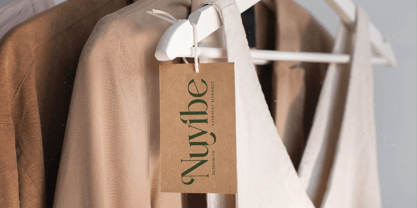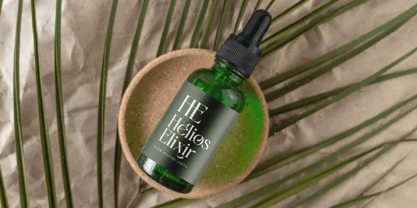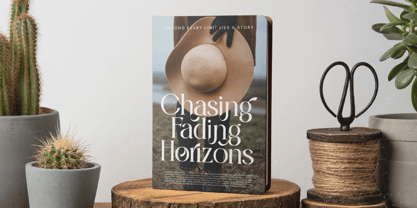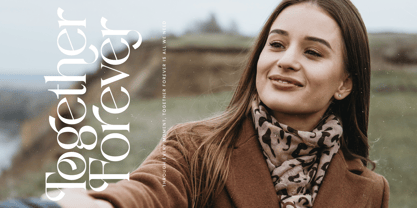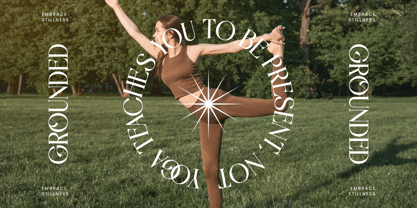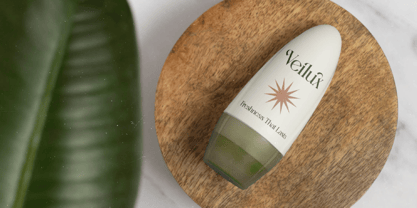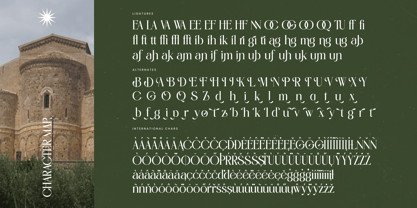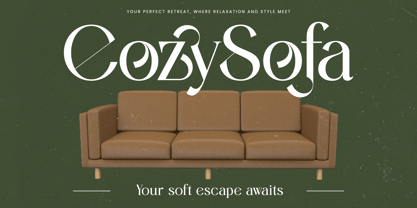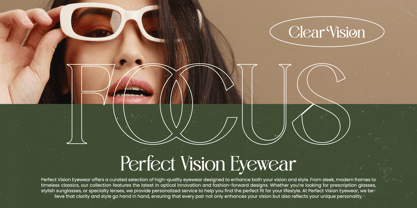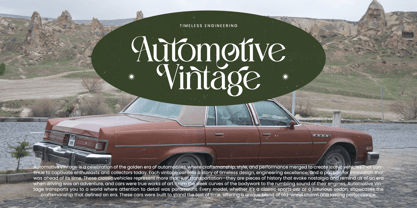
Kinetic Bravely
La familia tipográfica Kinetic Bravely fue diseñada por Heru Utama Putra y publicada por Timelesstype Studio. Kinetic Bravely contiene 2 estilos y opciones de paquete familiar. Más información sobre esta familia
Kinetic Bravely - Bold Tall Serif Font , from Timelesstype, Suitable for any projects such as: logos, branding projects, homeware designs, product packaging, mugs, quotes, posters, shopping bags, t-shirts, book covers, name card, invitation cards, greeting cards, label, photography, watermark, special events, and all your other luxury and beautiful projects that need a Luxury Serif taste.